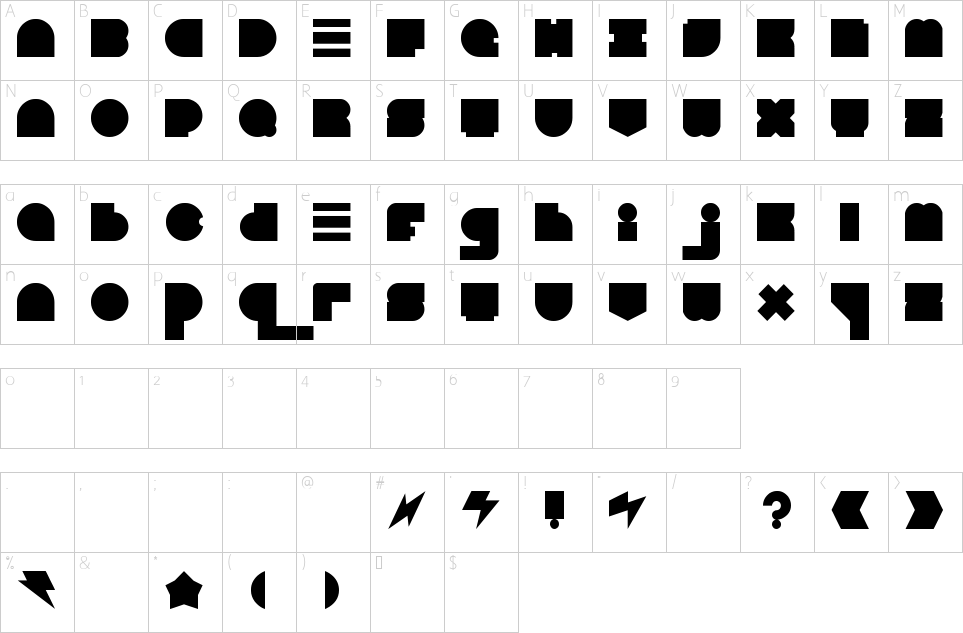
A Blast Beat Font é uma seleção perfeita para quem busca uma tipografia dinâmica e icônica que complementa a agressividade do seu design. Desenvolvida pelo designer Dirt2, esta fonte combina elementos modernos com um toque vintage, criando um estilo único que se destaca em qualquer projeto. Suas linhas apertadas e intercaladas são ideais para criar uma atmosfera intenso e emocionalmente ativa. Com a Blast Beat Font, você pode capturar o entusiasmo de uma bateria agressiva ou traduzir o poder do som no seu próximo design gráfico. Disponível tanto para Windows quanto Mac, esta fonte foi popular entre os designers que buscam um grito forte e único. Fique à frente com a Blast Beat Font.